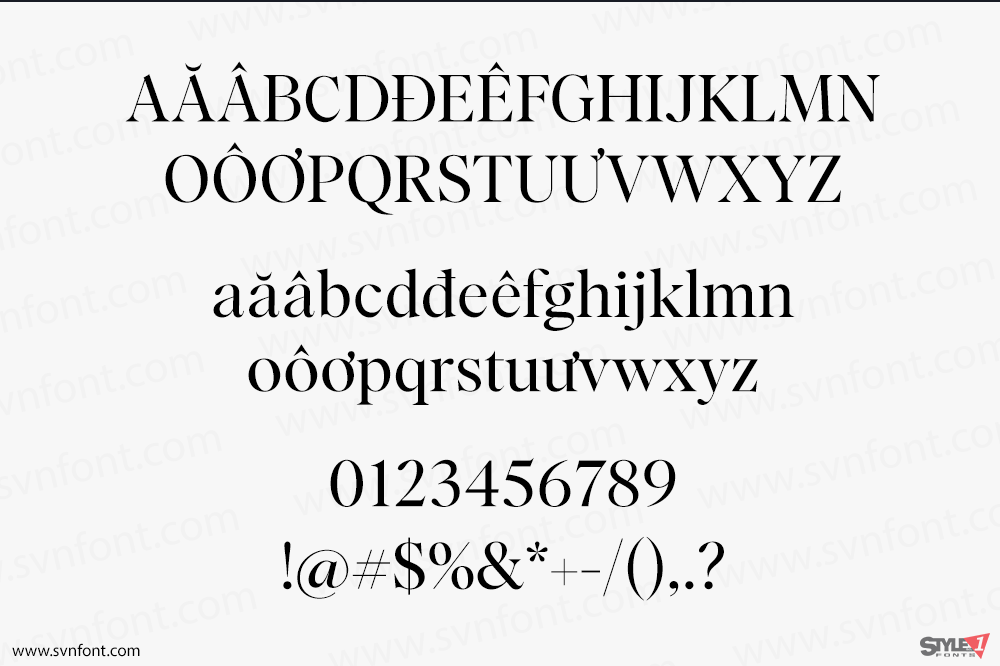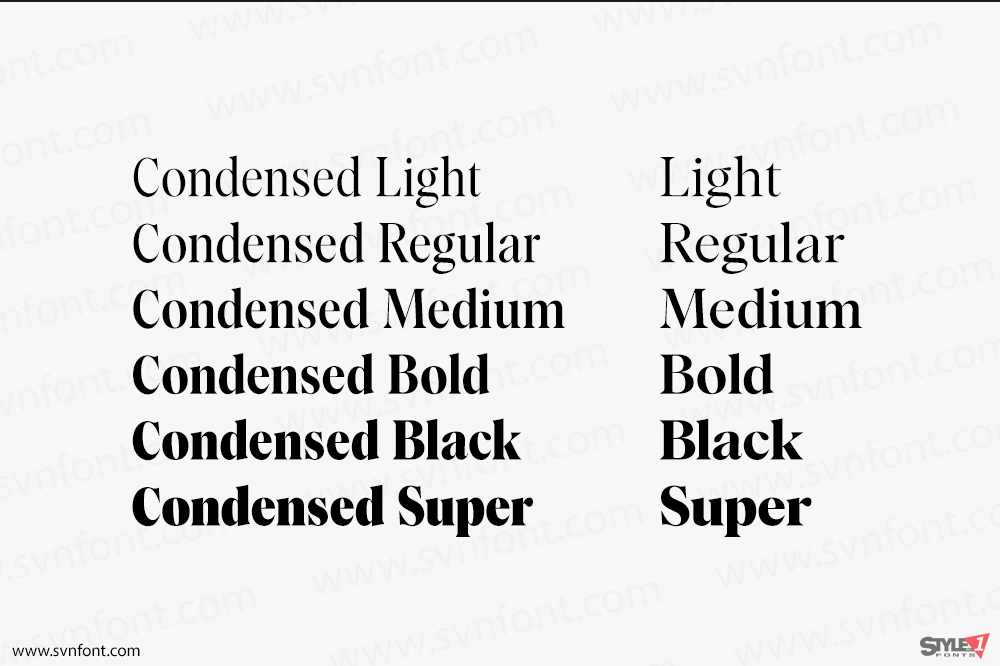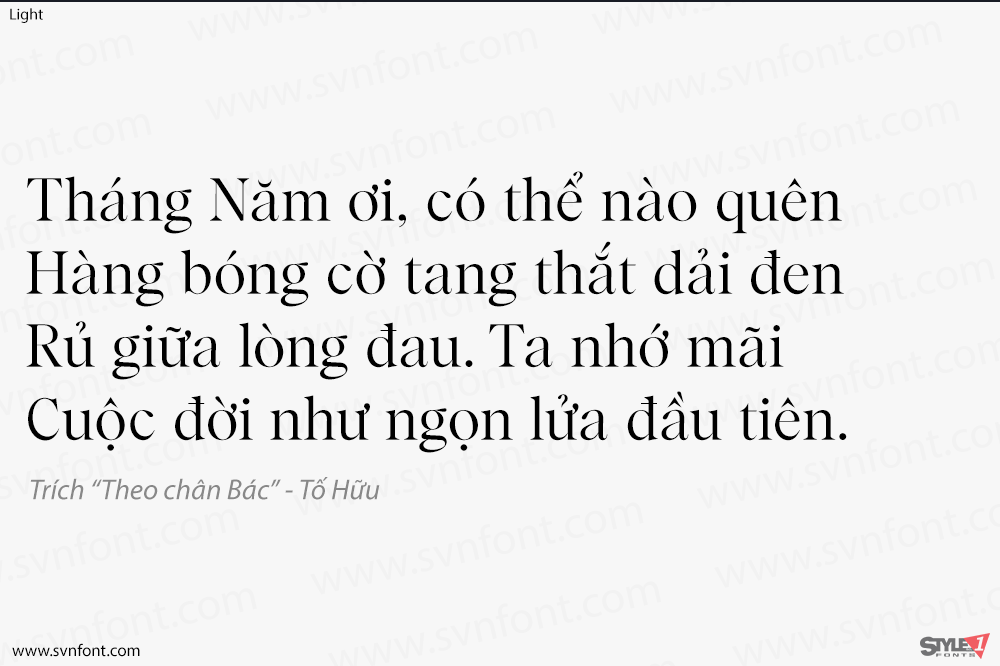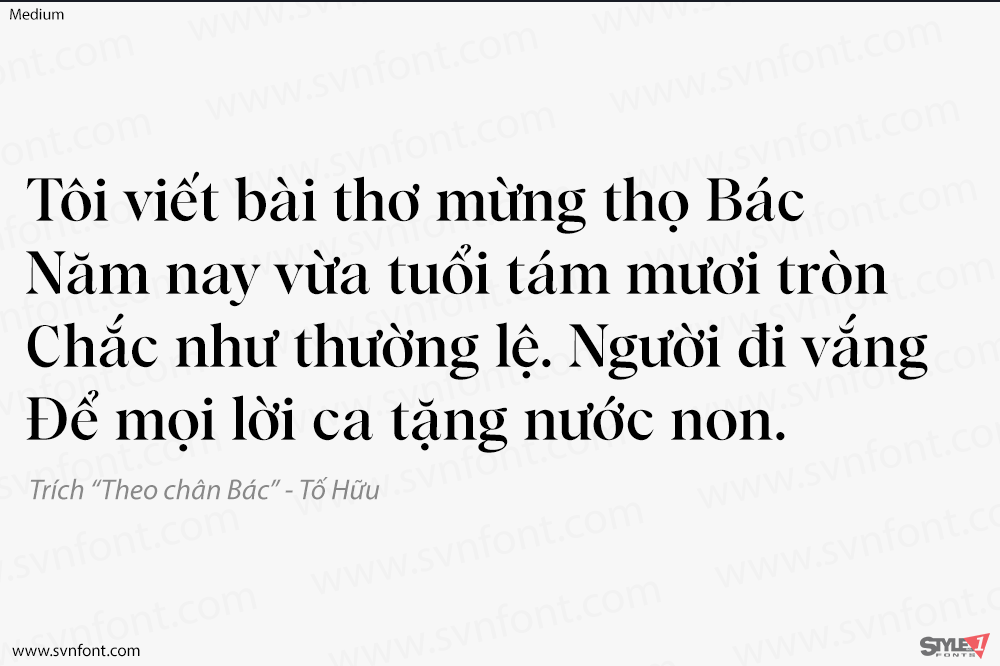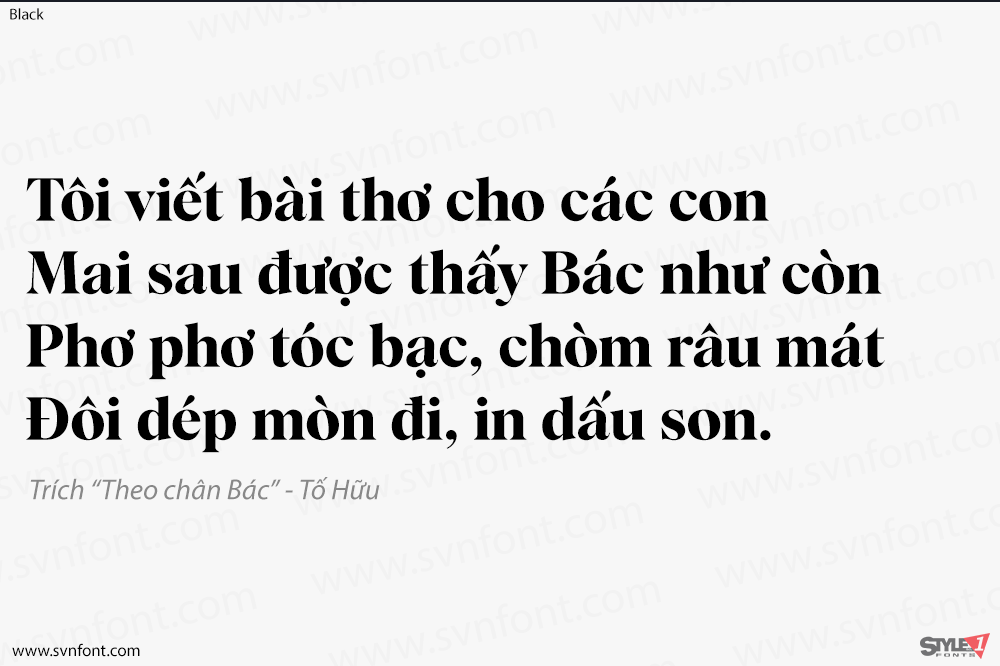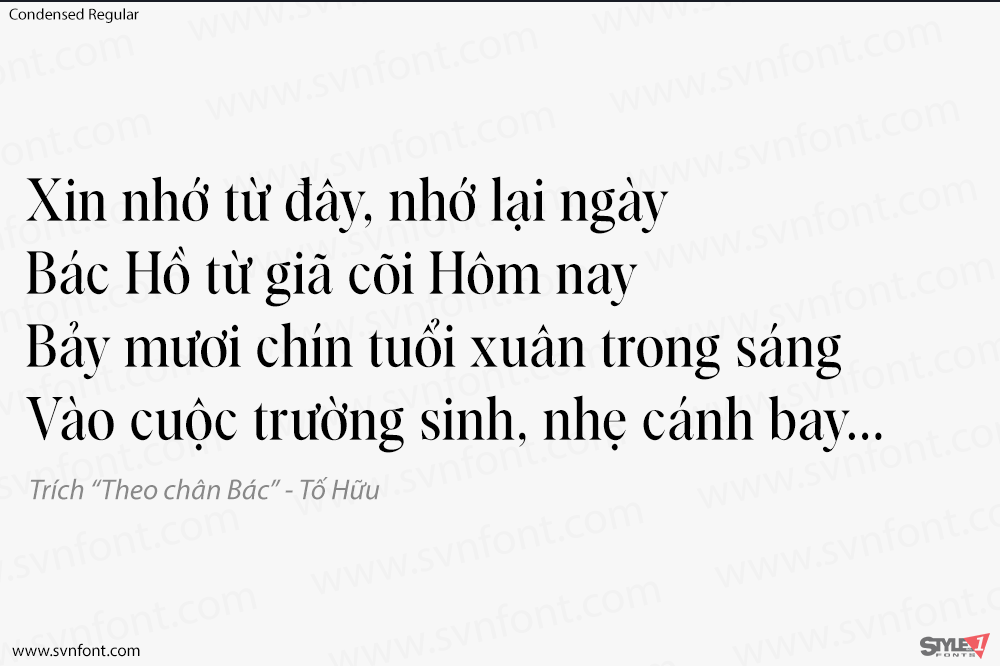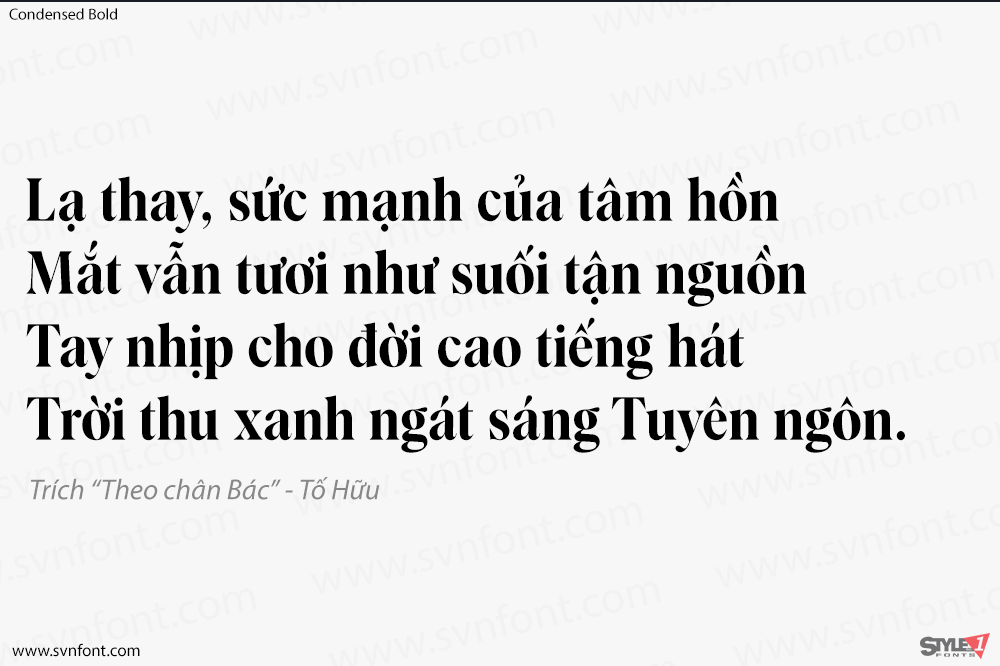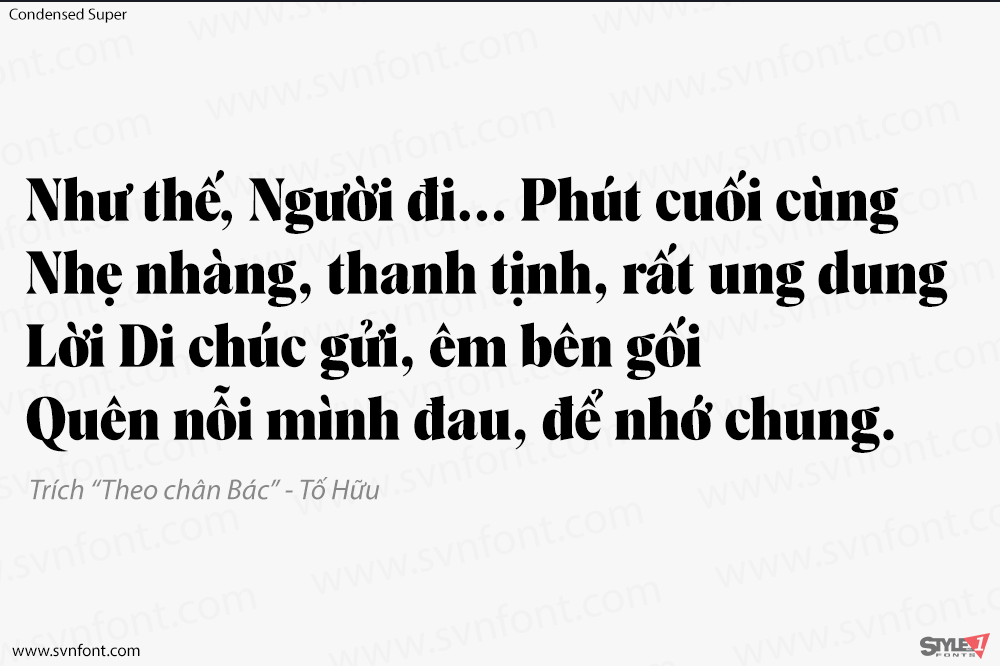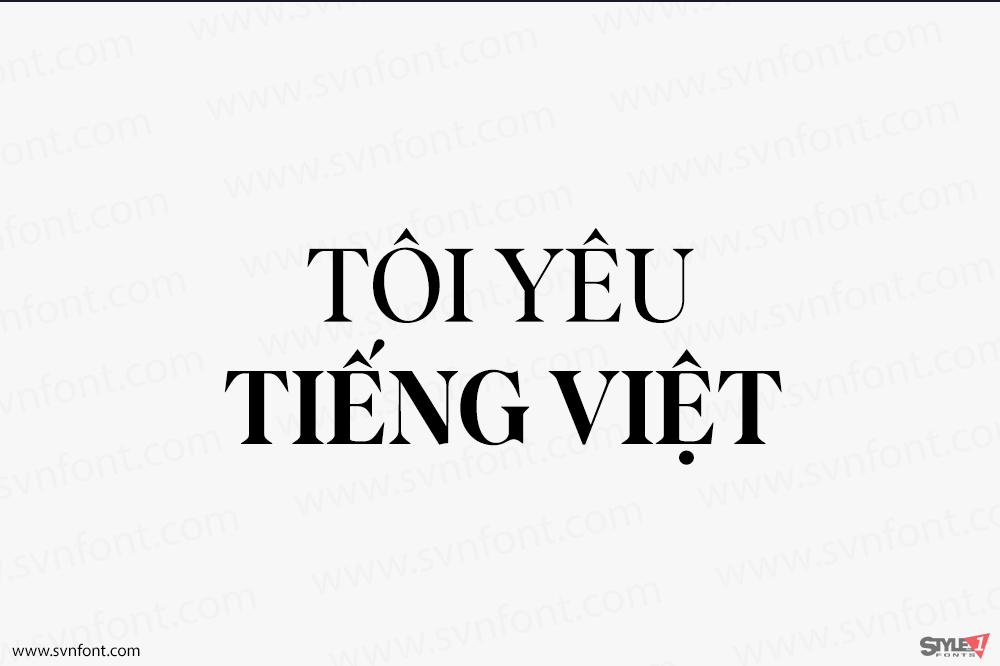
Matiere là kết quả của quá trình khám phá rộng rãi của chúng tôi về các kiểu chữ serif hiển thị có độ tương phản cao. Một nỗ lực để kết hợp đặc điểm của các chuyển động thư pháp với độ chính xác đương đại. Matiere gồm tổng cộng 12 fonts, trong đó 6 fonts thường và 6 fonts kiểu condensed. Font chữ thích hợp với thiết kế nội dung sách, báo, tạp chí…
Nhà thiết kế: Jan Weidemüller
Nhà phát hành: Ultra Kuhl